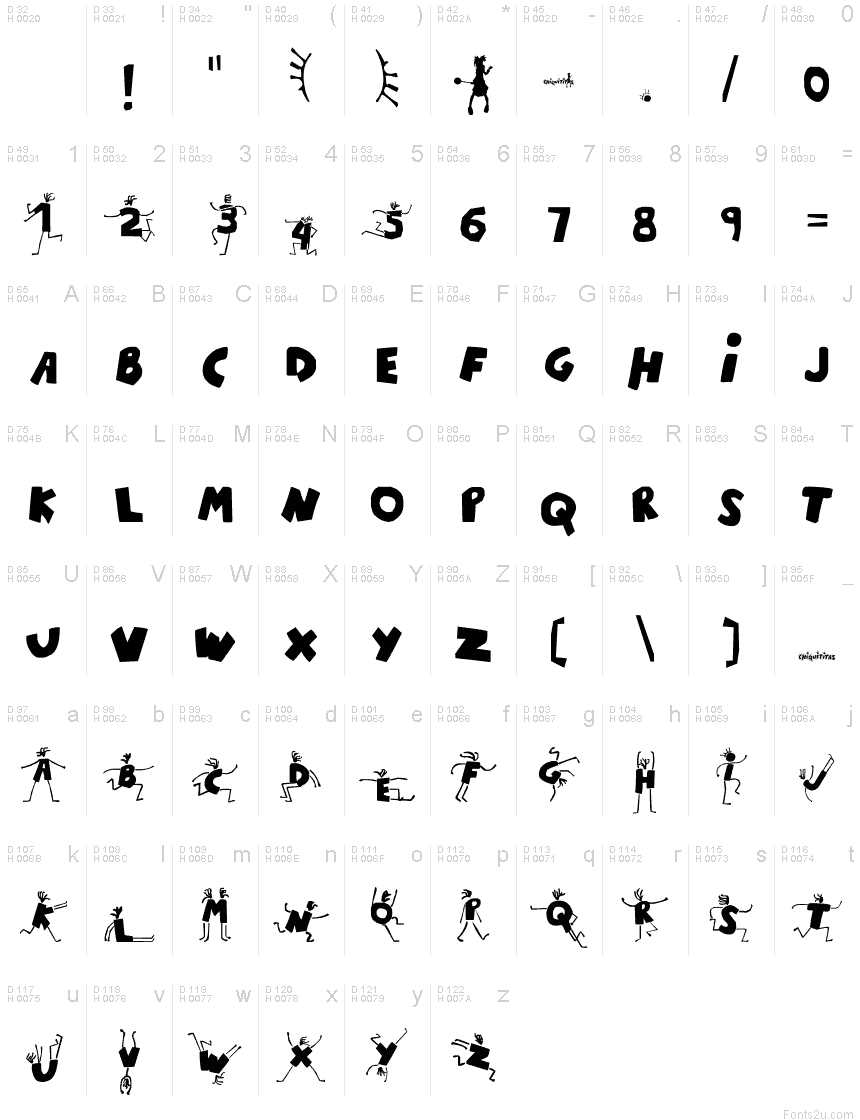
Chiqui Font to bezpłatny, zabawny krój typu display o rysunkowym, komiksowym charakterze. Litery łączą w sobie proste, masywne formy z „drucianymi” kończynami, małymi dłońmi i luźnymi gestami, dzięki czemu cały font przypomina raczej grupę ożywionych postaci niż zwykły zestaw znaków dekoracyjnych.
To sprawia, że jest to naturalny wybór do okładek książek dla dzieci, plakatów szkolnych, zaproszeń, tytułów komiksów czy nietuzinkowych znaków graficznych, w których żywe postacie same nadają ton. Sprawdza się również w krótkich nagłówkach i na tabliczkach z imionami, zwłaszcza gdy chcesz, aby same litery zachowywały się jak mali aktorzy.
Font de Chiquititas